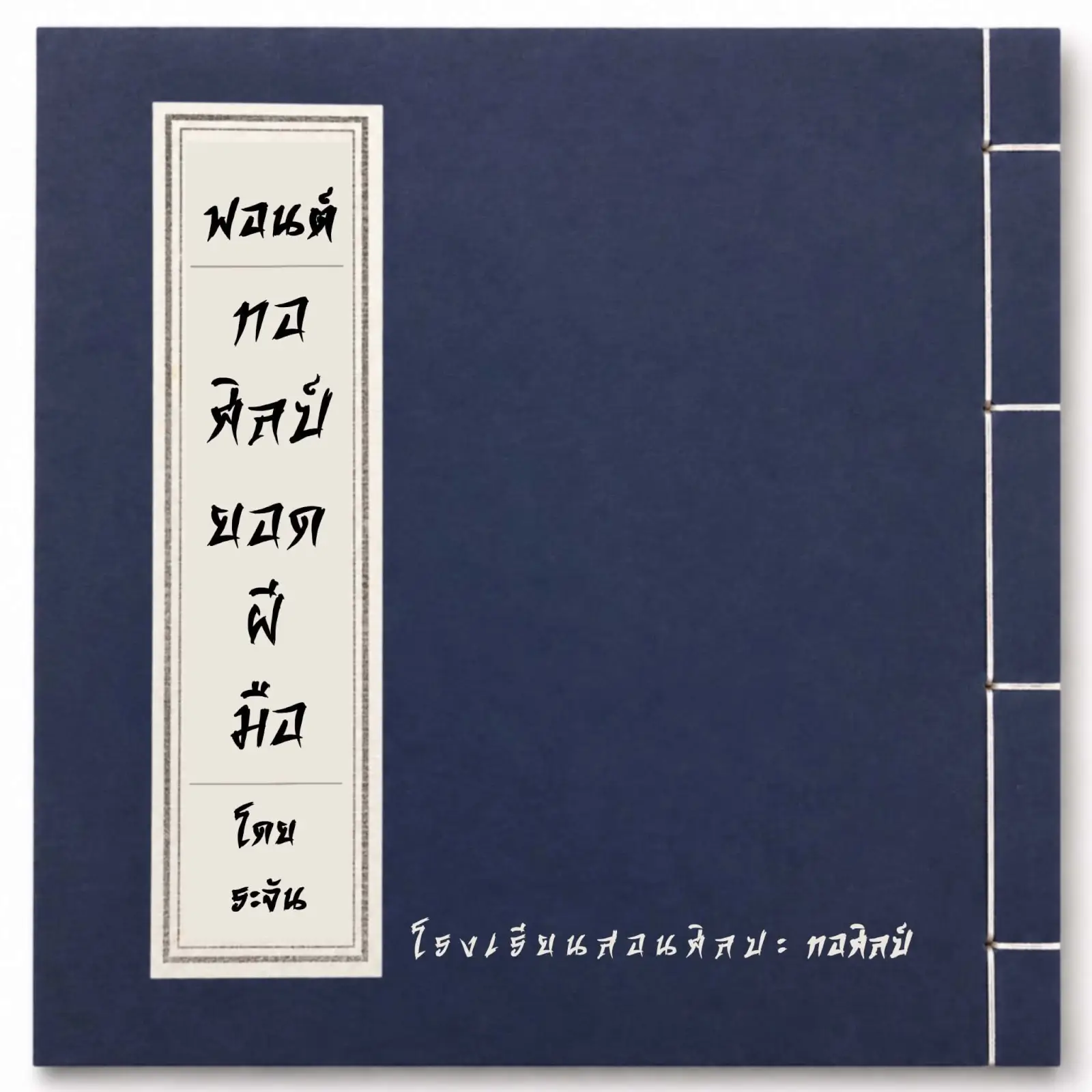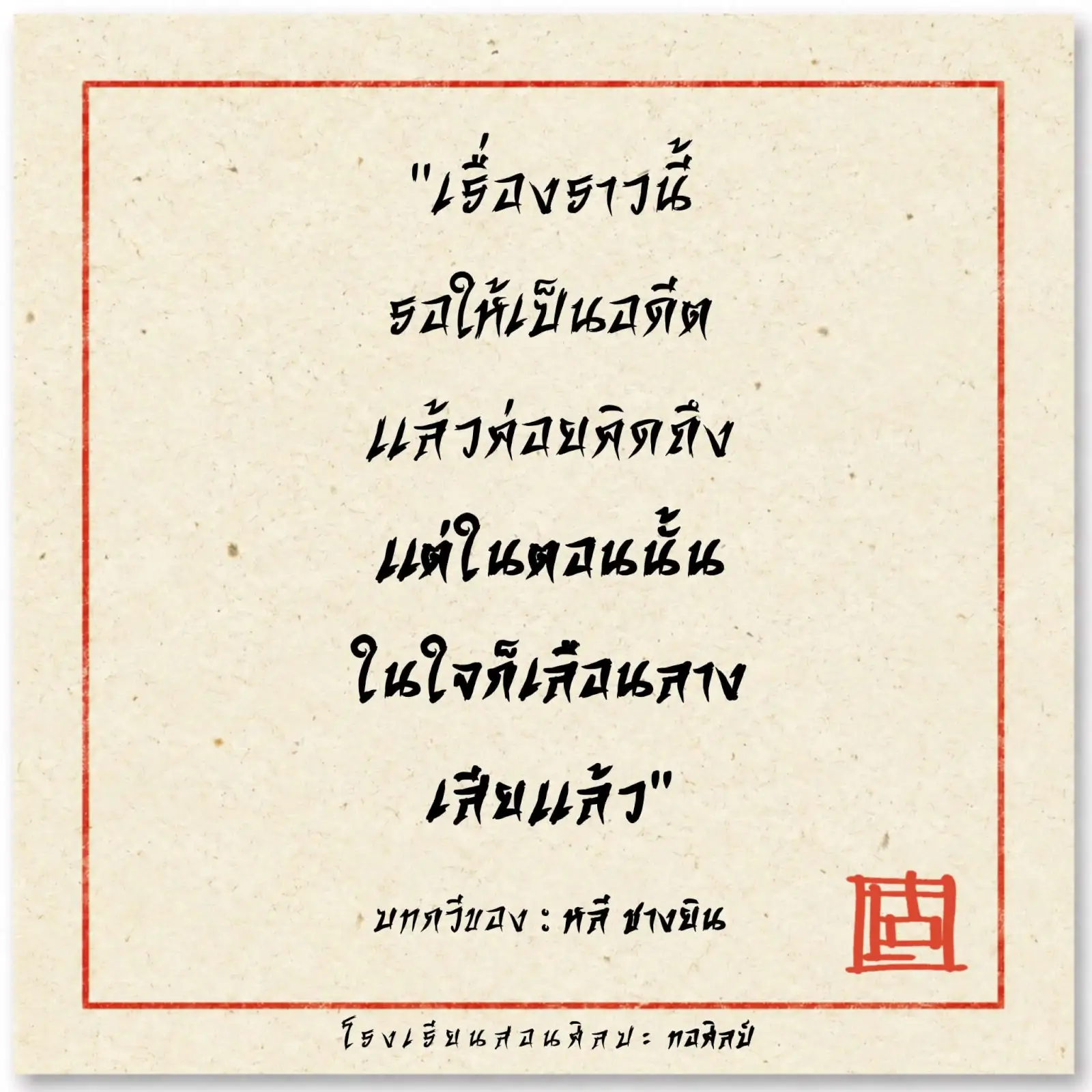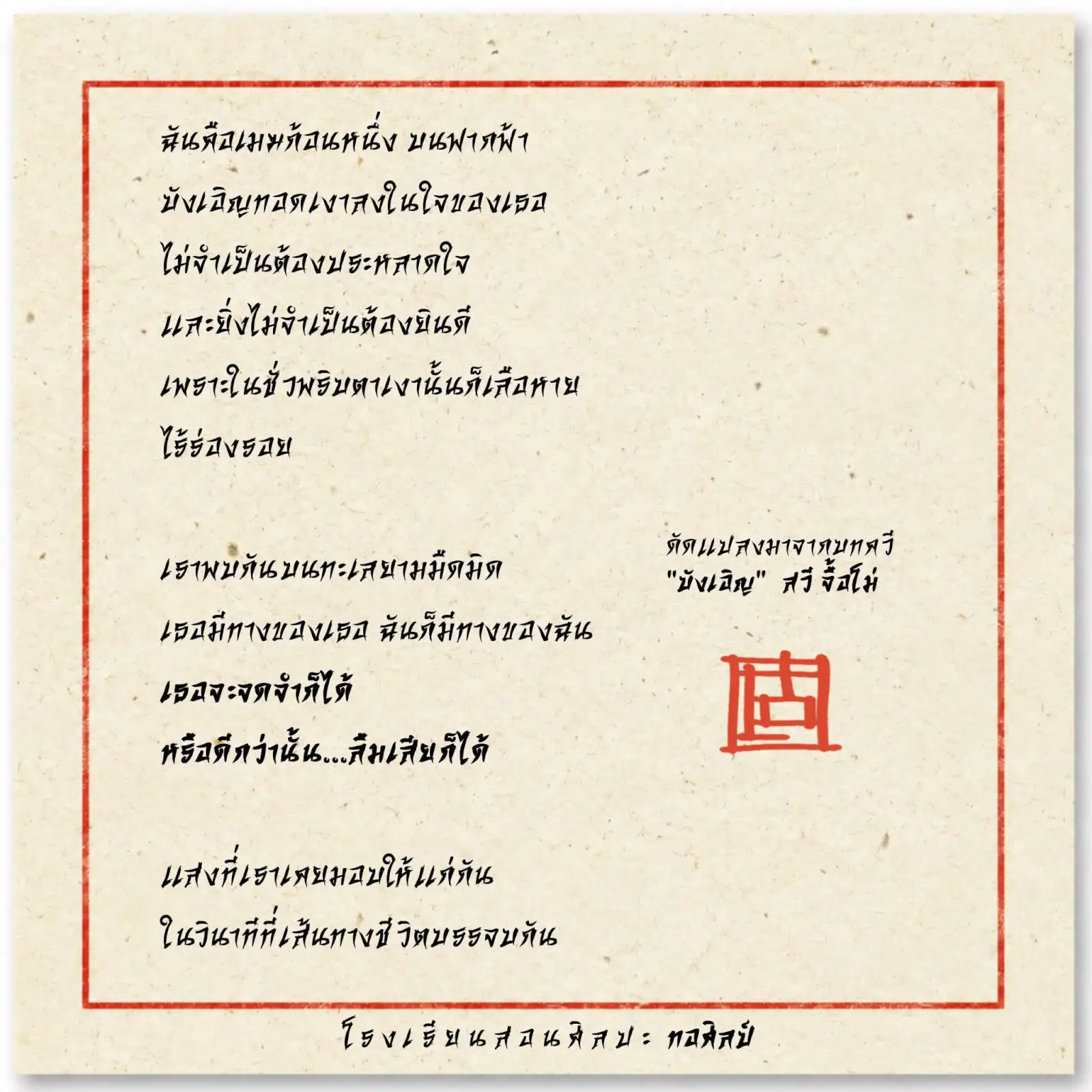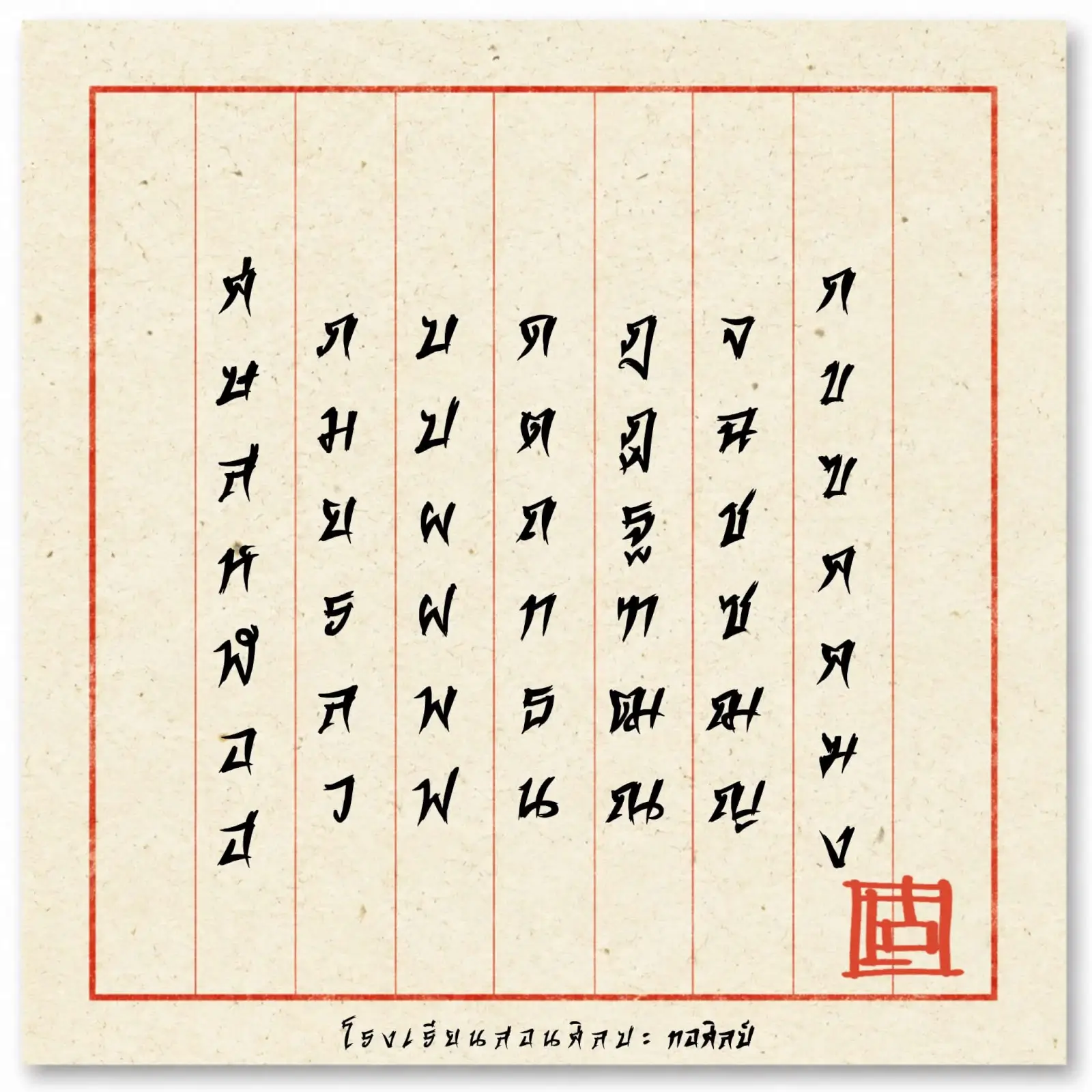
ฟอนต์ “ทอศิลป์ ยอดฝีมือ” เป็นฟอนต์รูปแบบสไตล์จีน เลียนแบบการเขียนพู่กันจีน ออกแนวยุทธภพ จอมยุทธ์
ฟอนต์โดย : ระจัน โรงเรียนสอนศิลปะทอศิลป์
ทอศิลป์ ยอดฝีมือ (Torsilp Yod Fimue)